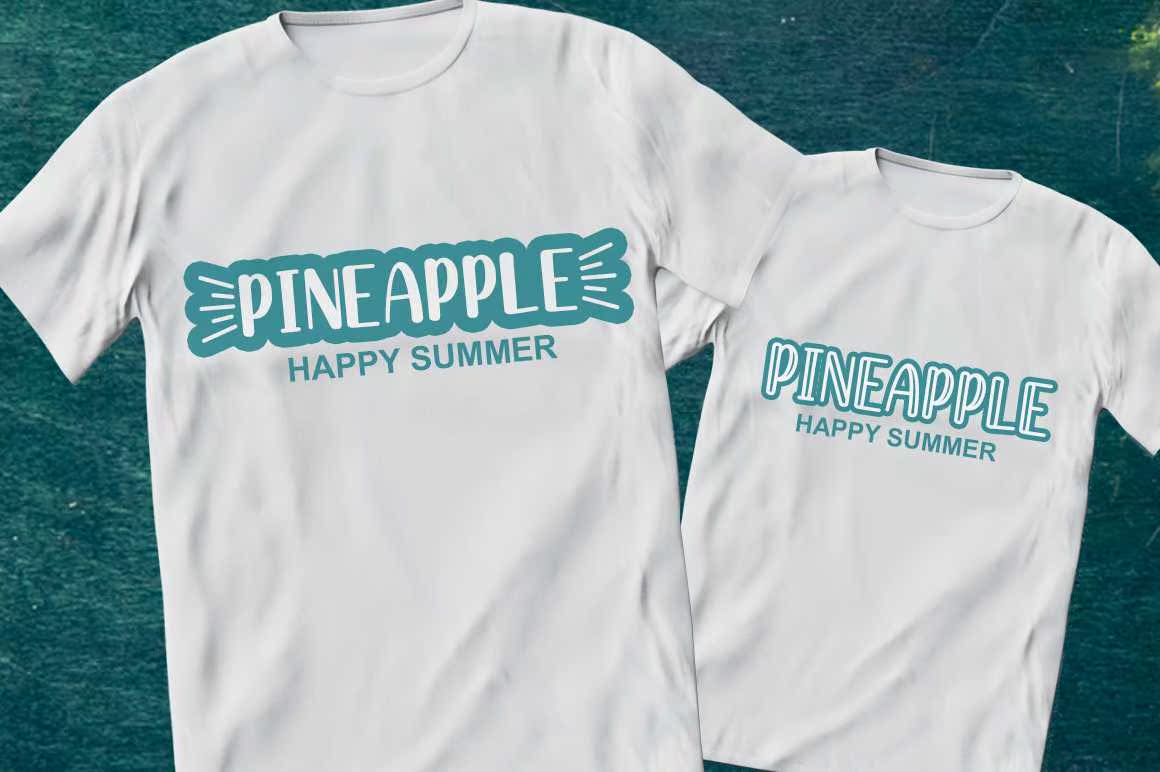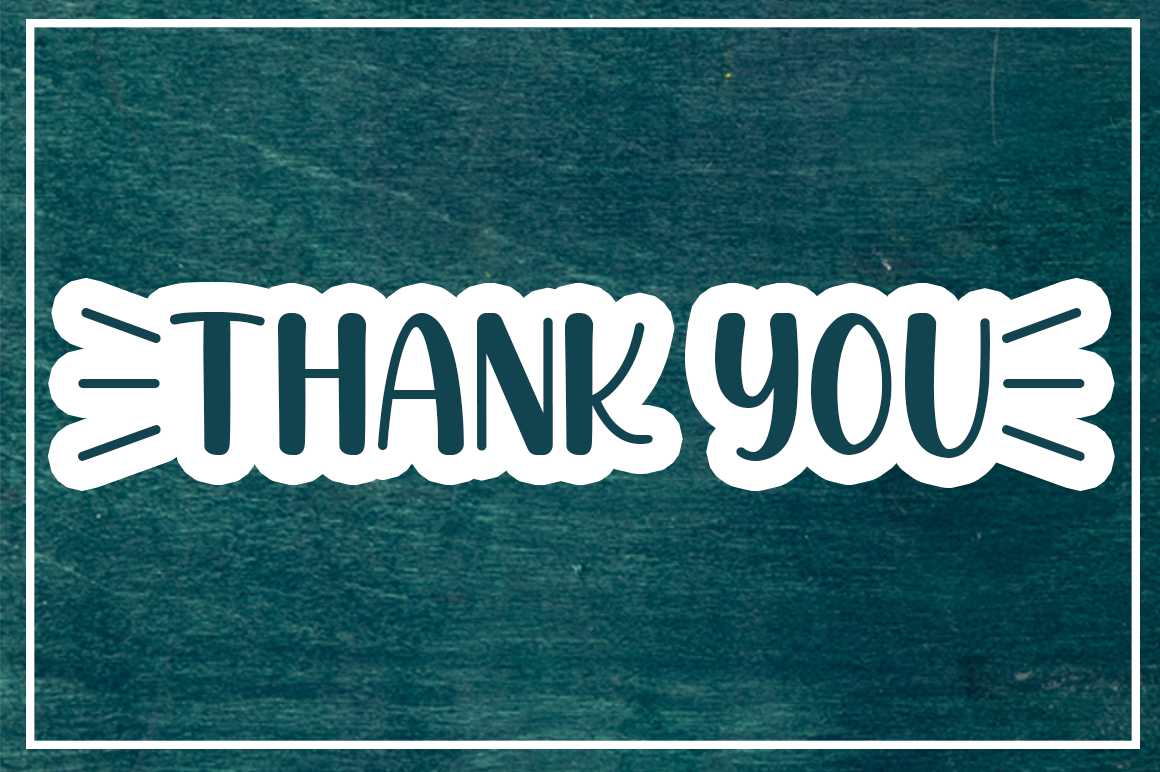
Hashed Brownsis and Write Tensans Font与所有大写字母拼贴,此Fonts看起来非常清晰,即使此Fonts可用于各种设计需求,它也可以作为设计主题。因为此Fonts具有用于数字化的所有字体类型,并且每个字体都非常清晰。Hashed Brownsis and Write Tensans Fonts与所有大写字母拼贴,此Fonts看起来非常清晰,即使该字体可用于各种设计需求,但它也可作为设计主题。因为该字体具有使AD数字化的各种不同类型,并且每个字体的纹理都更清晰。